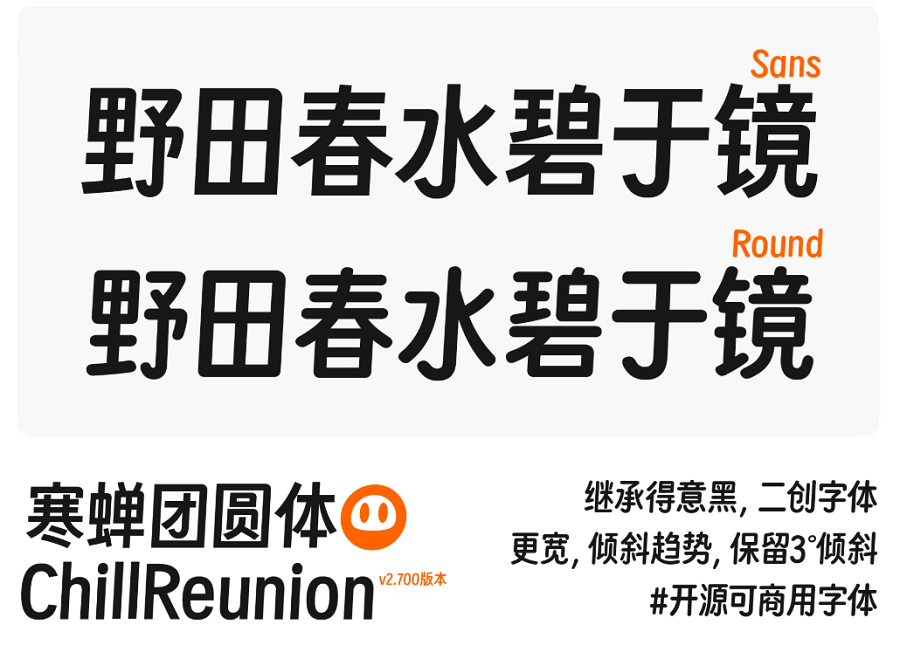
寒蝉团圆体(Chill Reunion)是一款由设计师萧熠 Siue(寒蝉字型)基于得意黑二次创作的开源可商用中文字体。
字体主打斜体和两种变体风格。斜体是在得意黑正体的基础上向右倾斜 3°(比常规斜体小),既有斜体的视觉效果又不影响长文本阅读;两种变体则分别为 Sans(锐利版)和 Round(圆润版)。前者笔画保持直角,仅字体右上角或竖钩处加入圆角处理,风格税利,适合做醒目大标题;后者笔画转角、端点处均呈圆角,更显亲和,适合副标题或正文排版。